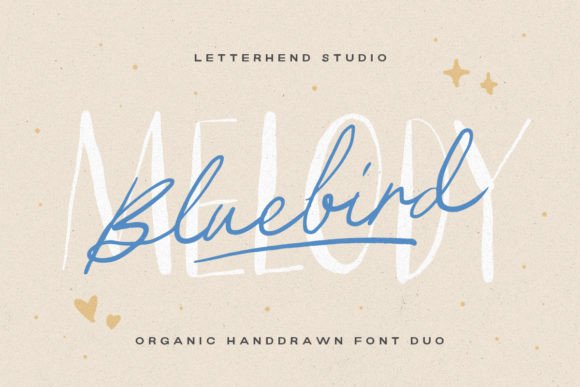
Bluebird Melody
適切なデザイン要素を見つけるのは難しい場合がありますが、Bluebird Melodyは作品を即座に引き立てる優れたコレクションを提供します。
POD(オンデマンド印刷)製品、結婚式の招待状、またはソーシャルメディアのグラフィックを作成している場合でも、Bluebird Melodyは理想的です。